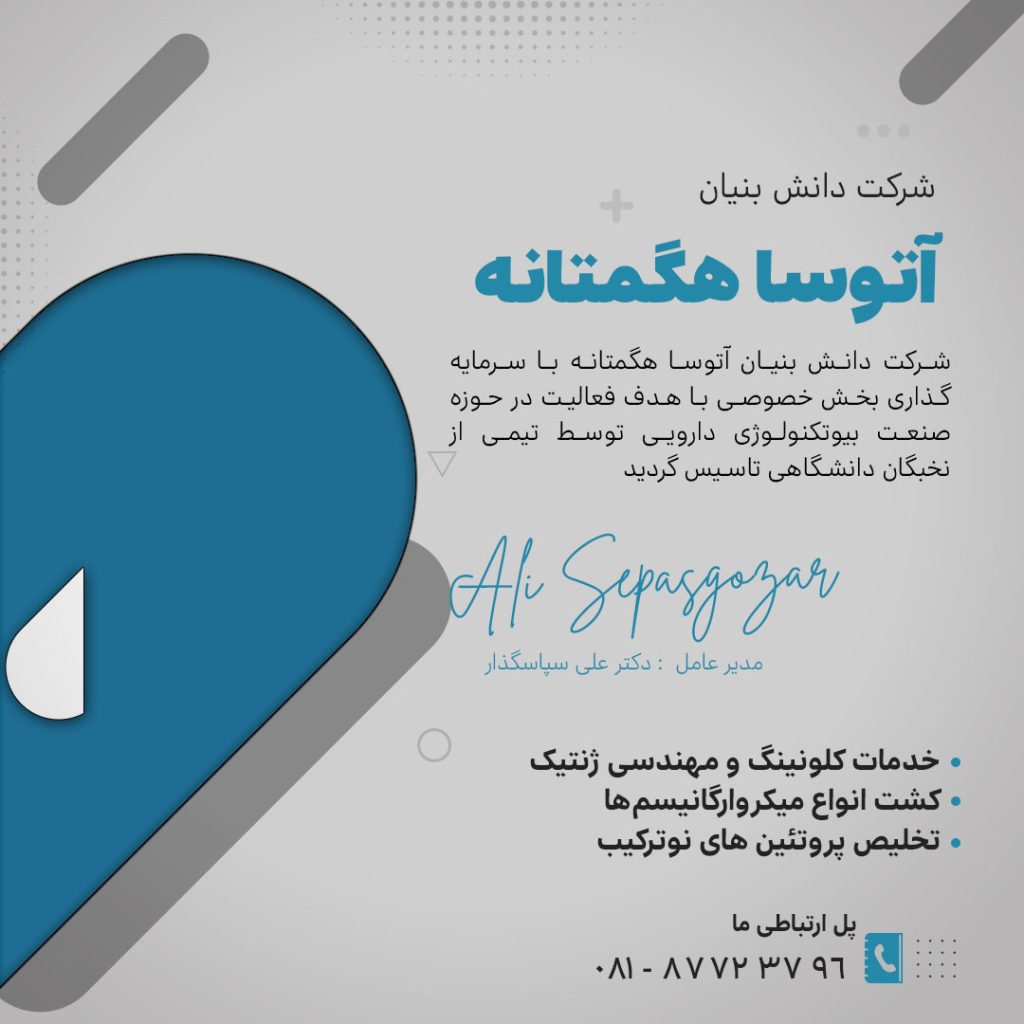
فونت وریبل مارلیک
فونت متغییر مارلیک دارای 9 وزن در با فرمت های مختلف و فایل جداگانه نسخه VF انتخابی مناسب برای مشتریان عزیز می باشد. مارلیک با ایجاد جاذبه برای خوانندگان و در عین حال سادگی همواره شجاعت را در بستر و بدنه محکم خود داشته و دارد.
فونت مارلیک از زبان فارسی، انگلیسی پشتیبانی میکند.